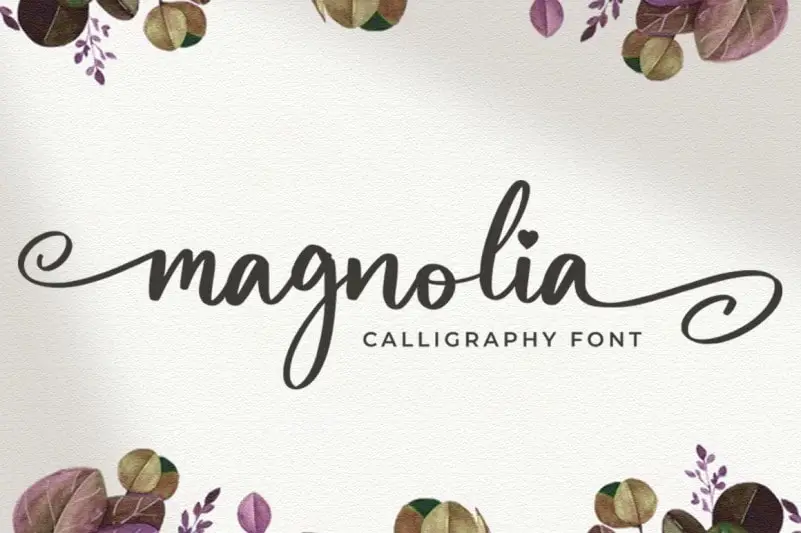
Magnolia Script Font é uma fonte que encanta os olhos por sua delicadeza e naturalidade, trazendo a essência do traçado manual com um toque de fantasia e leveza. Inspirada nas riquezas do hálito da contemporaneidade nos caracteres de escrita, ela vem equipada com uma ampla gama única de letras. Esta fonte é como encontrar o amor na primeira vista: encantadora, autêntica e cheia de vida, pronta para enriquecer qualquer projeto gráfico. Com ligaturas sofisticadas e estilos alternativos, Magnolia Script Font adicionará um toque único ao seu design, dando-lhe aquele charme especial que torna suas criações verdadeiramente únicas. Será uma fonte de inspiração para quem deseja dar um toque diferente à sua próxima peça gráfica.